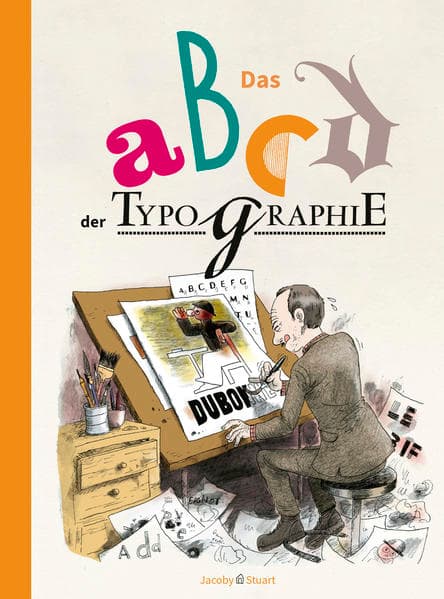
Das abcd der Typographie
Typographie ist das wichtigste Medium unserer Kommunikation Sie ist in Büchern, Zeitschriften, auf Plakaten und Bildschirmen allgegenwärtig, und das Internet besteht zu 95% aus Typographie. Aber was wissen wir eigentlich über dieses großartige Instrument? . Was hat unser Buchstabe A mit einem Ochsen zu tun? . Warum kommt uns ein Plakat, das die Comic Sans nutzt, weniger seriös vor als eins in der Trajan? . Woher kommt die Typographie, und welche Künstler haben sie geprägt? In diesem Buch beschreiben acht Zeichner auf leicht zugängliche und spielerische Weise die großen Etappen ihrer Geschichte, von der Entstehung der lateinischen Schrift bis zum Fotosatz, vom alten Rom bis zum Bauhaus und der DIN 1451.